「アンティーク・ビンテージ」な雰囲気にぴったりな日本語フォント
アンティーク・ビンテージなデザインでは、文字の質感が世界観を大きく左右します。古い紙に刷られたような明朝体、昭和の看板を思わせる太字、洋館や古書に似合うゴシック調の装飾文字など、フォント選びだけで画面の時代感や空気がぐっと深まります。
今回は、古いポスター、和風アンティーク、大正ロマン、ゴシックロマン、昭和ポップなど、クラシカルなアンティーク・ビンテージといった雰囲気を作りやすい日本語フォントをピックアップしました。
ロゴや見出し向きの個性派から、文学的な本文にも使いやすい明朝体まで、ビンテージ表現に合わせて選べるように紹介します。
アンティーク・ビンテージ風デザインに使いやすい日本語フリーフォント
テンケイ
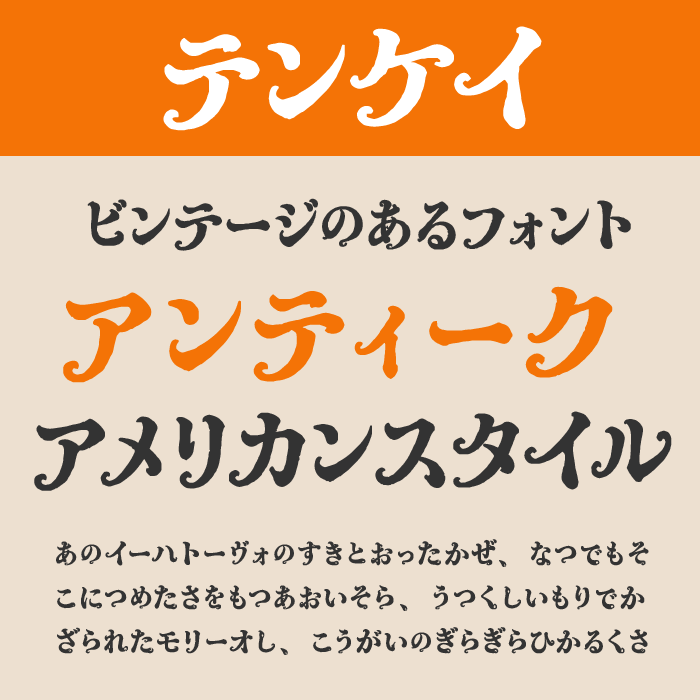
テンケイは、筆の流れを感じるしなやかな字形と、どこか古風な空気が魅力の日本語フォントです。
太すぎず細すぎない線の抑揚があり、和風のアンティーク感や、昔の本の表紙のような落ち着いたムードを作りやすい一本です。ビンテージ調のデザインでは、喫茶店のメニュー、和菓子のパッケージ、文学的なタイトル、古いポスター風の見出しなどに向いています。
だるまドロップ
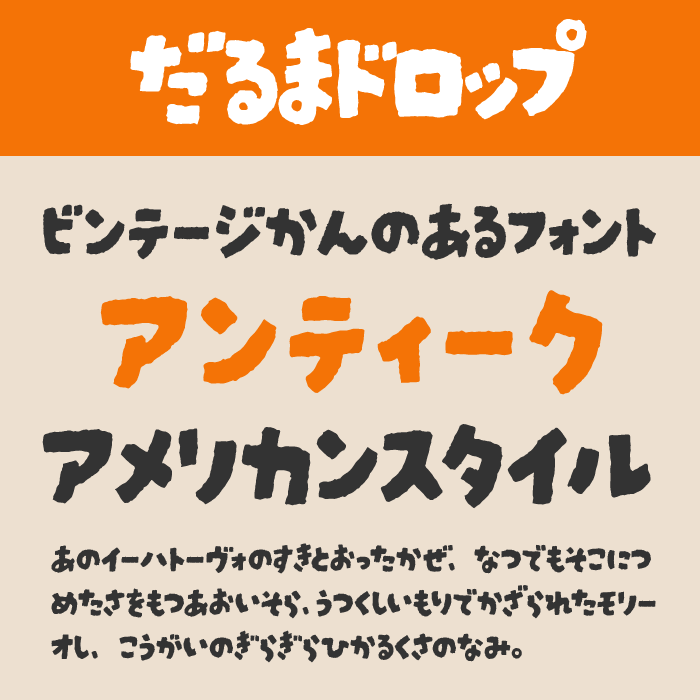
だるまドロップは、だるま落としのような民芸感と、手描きの温かさを感じるデザインフォントです。
丸みのある太い字形に筆跡のラフさが加わり、昭和の玩具や駄菓子屋、古い土産物ラベルのような親しみやすい雰囲気を出せます。漢字は収録されていないため、短いかな文字の見出しや、ロゴ的な使い方がおすすめ。和風ビンテージを明るく見せたいときに活躍します。
めもわーる
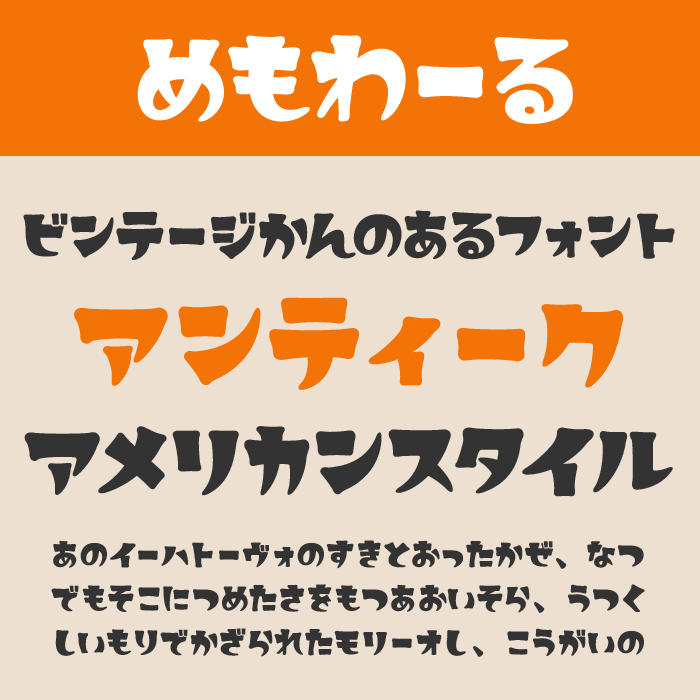
めもわーるは、ころんとした太い丸文字に、レトロでファンシーな可愛さを感じるフォントです。
アンティークというよりは、昭和の雑貨や昔のお菓子パッケージのような、少し甘く懐かしいビンテージ感に向いています。短い言葉を大きく置くだけで存在感が出るので、喫茶店メニュー、レトロポップな見出し、手作りラベル、SNS画像のタイトルにも使いやすい一本です。
金魚ランタン
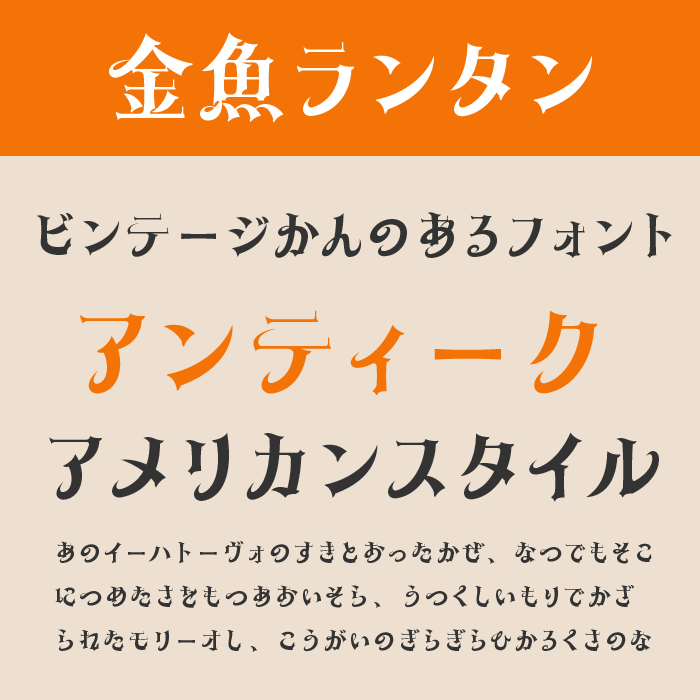
金魚ランタンは、ブラックレターの雰囲気を日本語に落とし込んだ、装飾性の高いデザインフォントです。
鋭いハネや払いが印象的で、洋館、古書、夜会、ゴシック調のポスターなど、少し幻想的で重厚なアンティーク表現によく合います。細部に個性があるため、本文よりもタイトルやロゴで大きく使うのがおすすめ。無料のmini版は利用範囲が限られるため、商用利用時は必ず製品版や規約を確認したいフォントです。
シャランラ
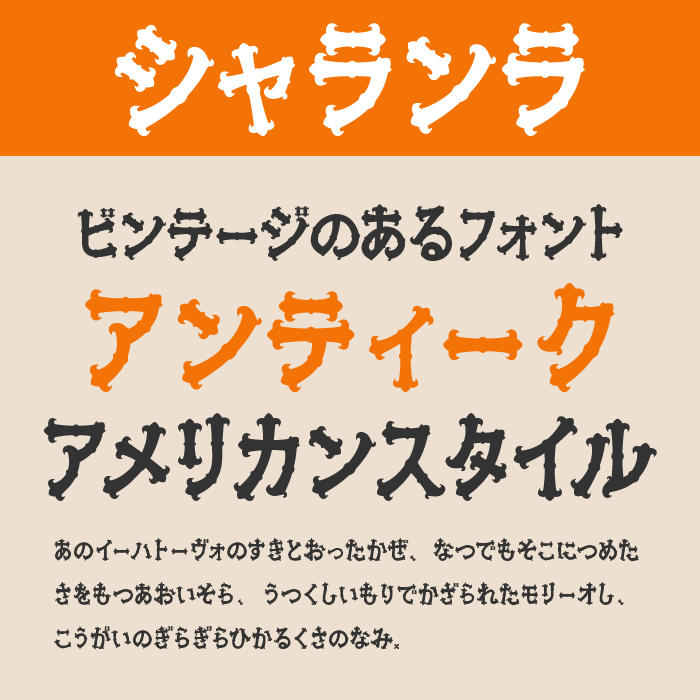
シャランラは、少女漫画のきらびやかさを思わせる装飾的なフォントです。
文字の端に華やかな揺れや飾りがあり、古い少女雑誌、洋菓子店のラベル、ロマンチックな雑貨パッケージのような雰囲気を作れます。漢字は収録されていないため、短いかな文字のタイトルやロゴ向き。アンティーク系の中でも、可憐で少し夢見がちなビンテージ感を出したいときにぴったりです。
MiFファイト
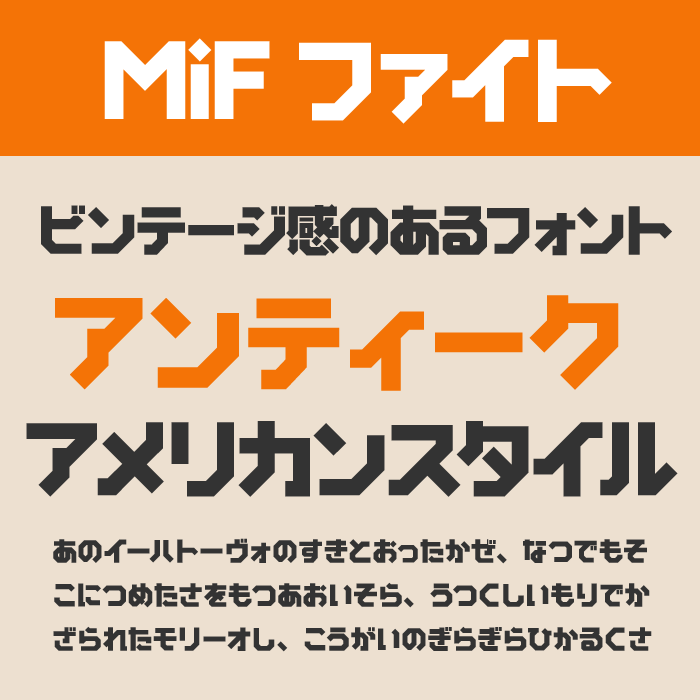
MiFファイトは、直線的でカクカクした骨格が印象的な、力強いデザインフォントです。
アンティーク・ビンテージの中でも、古い映画ポスターや昭和SF、工業製品のロゴ、アメリカンな看板風デザインに向いています。硬質でスピード感があるため、クラシックな明朝体とは違う方向の懐かしさを出せるのが魅力。無料版は漢字なしなので、短いタイトルやカタカナ見出しで使うと映えます。
叛逆明朝
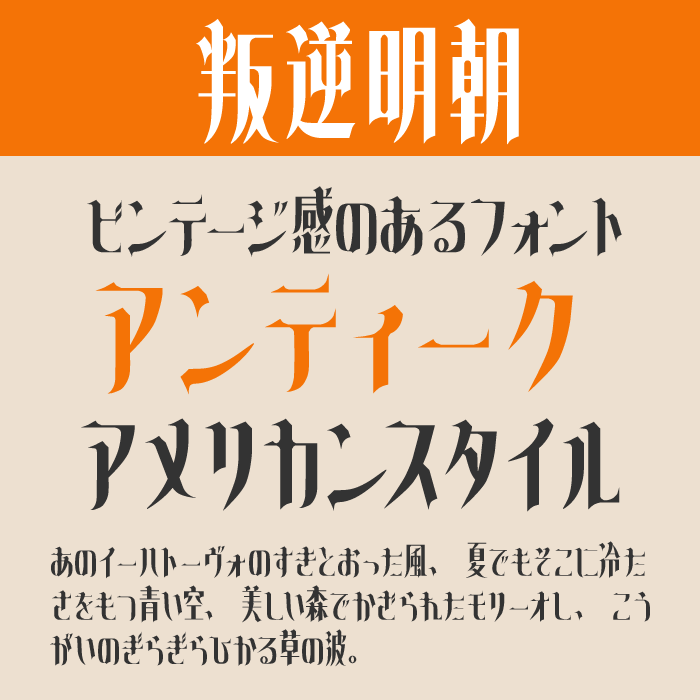
叛逆明朝は、明朝体の品格に鋭い装飾を加えた、エレガントで反骨的な雰囲気のフォントです。
細く尖ったエレメントが印象的で、古い洋館、ゴシックロマン、退廃的な舞台ポスター、クラシカルな物語タイトルによく合います。上品さと不穏さが同居しているため、ただ古いだけではない、少しドラマのあるビンテージ表現を作れるのが魅力。大きめのタイトルで使うと存在感が出ます。
ニューテゴミン
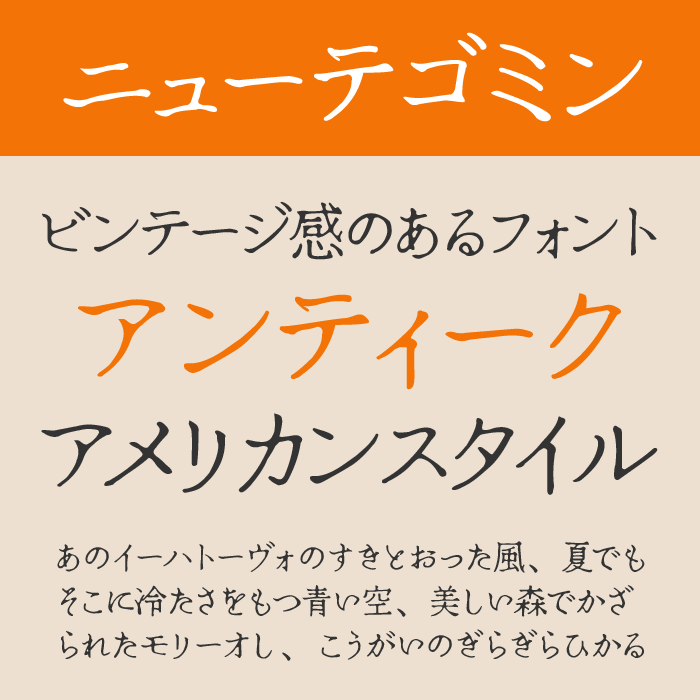
ニューテゴミンは、筆のしなやかさを感じる、やさしい明朝系フォントです。
線の流れが穏やかで、文学的なタイトルや、古い手紙、詩集、喫茶店のメニューのようなデザインにしっくりなじみます。アンティーク・ビンテージ用途では、強く目立たせるよりも、余白を活かして上品に見せる使い方がおすすめ。大正ロマンや昭和初期の印刷物を思わせる、静かな懐かしさを演出できます。
金畫字
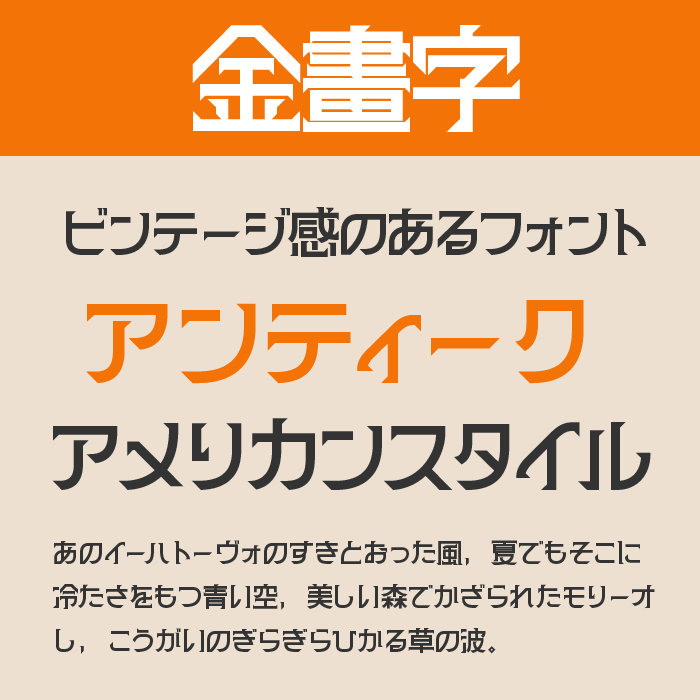
金畫字は、縦・横・斜めの直線を主軸に、三角形のエレメントで構成された個性的なフォントです。
幾何学的な硬さと装飾性があり、アールデコ調の見出しや、古い金属看板、銘板、老舗ブランドのロゴ風デザインに向いています。ビンテージ感を出しつつ、和風に寄りすぎないモダンな重厚感を作れるのが魅力。大きく使うほど細部の形が引き立つ、タイトル向きの一本です。
さつき源代明朝
さつき源代明朝は、古典的な筆致と現代的な読みやすさが同居した、やわらかい明朝体フォントです。
文字の流れに品があり、古書、手紙、文学作品の装丁、和風パッケージなど、静かな時間を感じるアンティーク表現に向いています。派手な装飾で見せるというより、言葉そのものに余韻を持たせたいときにぴったり。落ち着いた紙色や墨色と合わせると、上質なビンテージ感が出せます。
Potta One
Potta Oneは、筆文字をもとにしたような、丸くぽってりした形が印象的なデザインフォントです。
少し溶けたような柔らかい輪郭があり、昭和のお菓子箱や、手描き看板、レトロ喫茶の見出しにぴったりです。堅いアンティークではなく、親しみやすくポップなビンテージ感を出したいときに使いやすい一本。短いタイトルを大きく配置すると、温かく楽しい印象に仕上がります。
略字超少明朝穴
略字超少明朝穴は、明朝体をベースにした荒れやかすれの質感が印象的なデザインフォントです。
ところどころ欠けたような表情があり、古い印刷物、朽ちた看板、退廃的なポスター、ミステリー系のタイトルに向いています。アンティーク・ビンテージ用途では、きれいな古さではなく、時間で傷んだ紙やインクのような雰囲気を出せるのが魅力。力のある見出しで使いたいフォントです。
黒薔薇ゴシック
黒薔薇ゴシックは、ゴシック体の骨格に薔薇の棘のような装飾を加えた、華やかで少し毒のあるフォントです。
鳩とブリキのワンダランド
鳩とブリキのワンダランドは、極太のシルエットと、少し不揃いな文字の動きがかわいいレトロ系フォントです。
ブリキのおもちゃ、昭和の看板、古い喫茶店のポスター、お菓子パッケージのような、懐かしくて親しみやすいビンテージ感を作れます。本文には向きませんが、短いタイトルや大きな見出しではかなり強い存在感があります。無料版は収録文字が限られるため、使う文字数に応じて確認しておきたい一本です。